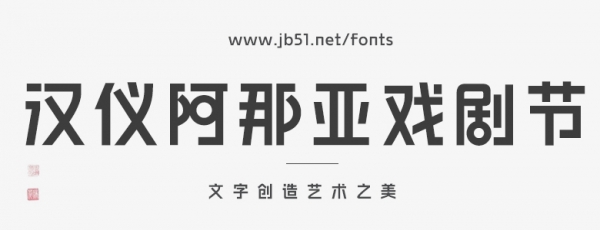
“汉仪阿那亚戏剧节体”是汉仪字库与阿那亚戏剧节联合打造的首款以戏剧节为题材的专属品牌字体。字体基于戏剧节LOGO的视觉语言延展设计,以无衬线黑体为结构基础,通过符号化设计传递戏剧艺术的核心精神。
整体字形强调几何块面与清晰识别,以采用几何圆形为核心特征。
设计将单字视作“微型舞台”进行重构,在字面比例、笔画粗细与留白节奏之间建立精密秩序,在保持粗黑体力量感的同时,削弱其压迫感,使字形更具呼吸感与节奏性,从而强化品牌识别与叙事能力。
字体在风格上呈现简约而有力的现代特征,精准传递戏剧艺术的先锋气质与视觉力量。